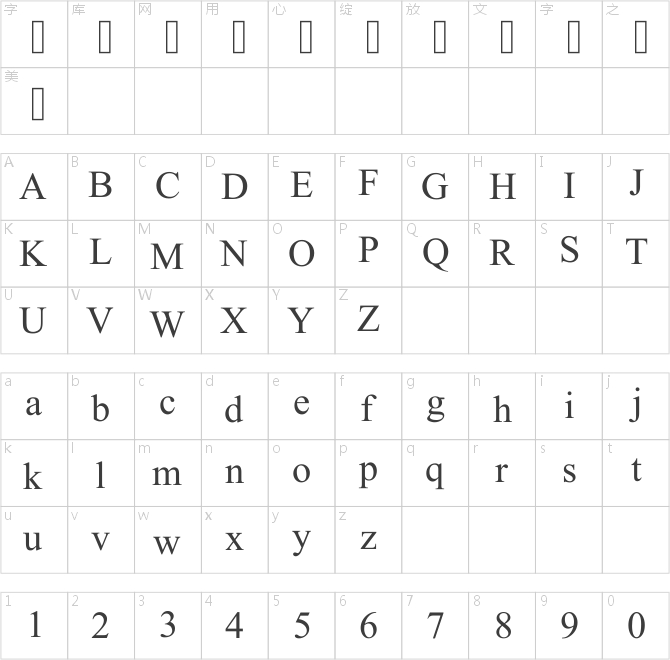
迷藍藏文藝術
迷藍公司董事長次仁扎西表示,公司始終把培養合格社會主義建設者和接班人作為根本任務,為廣大高校畢業生提供就業擇業平臺,目前我公司就業帶動34人,其中大學生占27人。在過去三年的時間里公司專注于藏文藝術體的研發,始終秉承以人民為中心的創作導向,堅持創作無愧于時代的優秀作品,此次面向社會共發布了14種字體,分為兩種類型:傳統型字體與藝術型字體,整個字體的考察、收集、研發、編輯到錄入,工程為期將近三年左右,其參考了桑耶寺的石碑字體及布達拉宮的壁畫字體等。